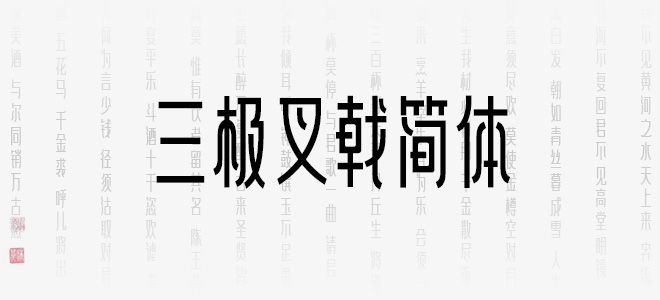
三極叉戟簡體靈感來源于商周文化,結(jié)合了冷兵器時(shí)期的建筑,服飾與青銅器的紋路而形成的三極戟黑簡體,字體復(fù)古,極具商周色彩。適用于個(gè)性海報(bào)設(shè)計(jì),復(fù)古風(fēng)格包裝設(shè)計(jì)等。歡迎喜歡三極叉戟簡體的朋友前來下載使用。
三極叉戟簡體